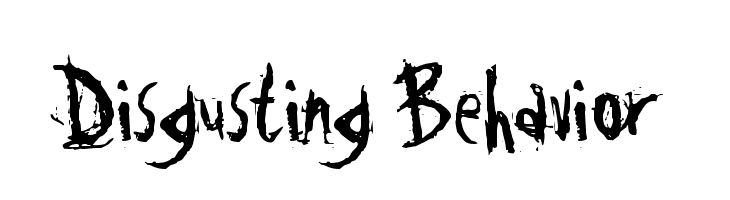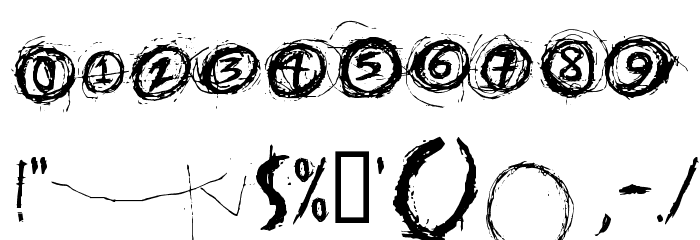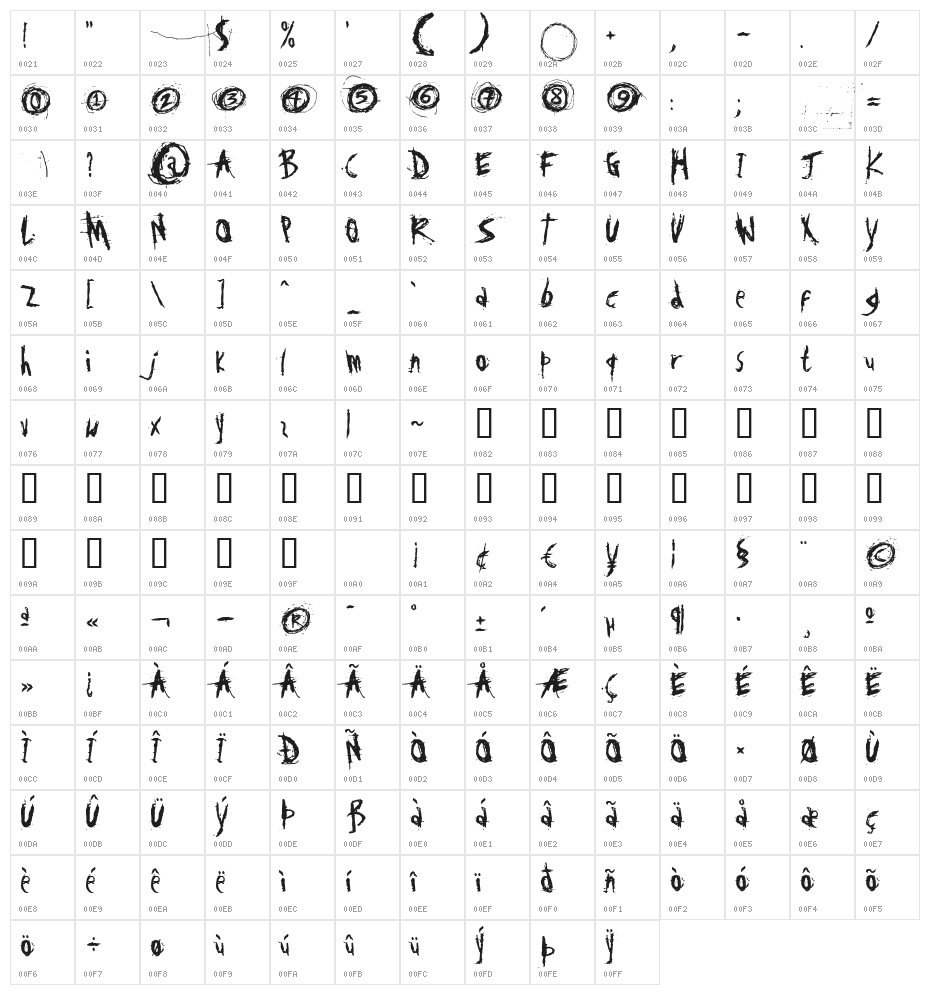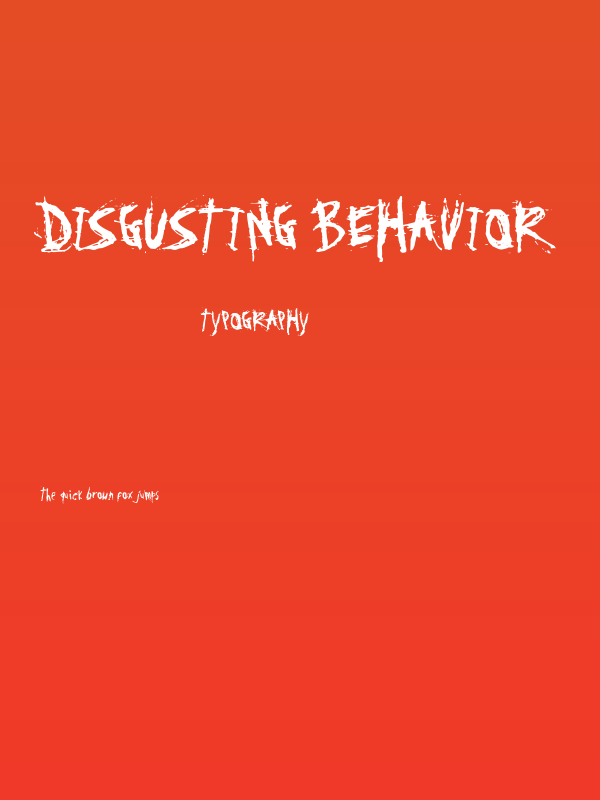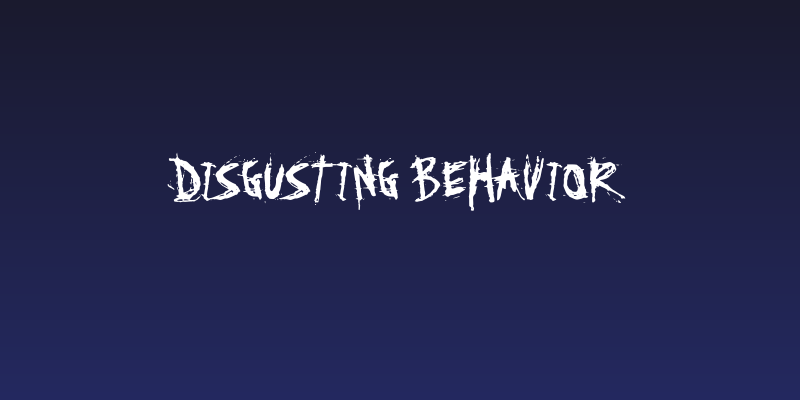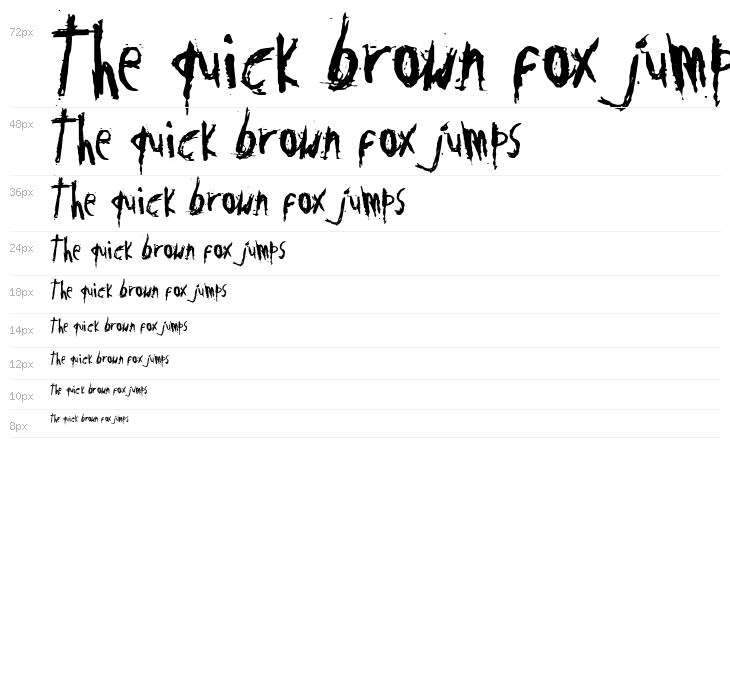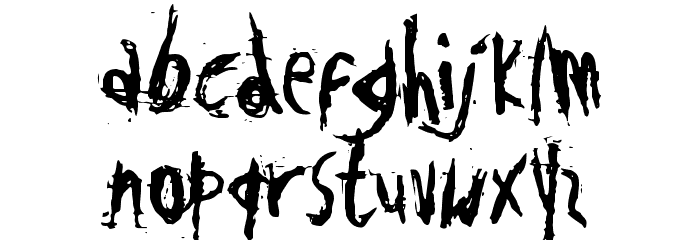
Disgusting Behavior Font
| Gesamtstil | Grunge, Edgy, Rebellious |
| Anwendungsfall | Headlines, Posters, Branding |
| Vorgeschlagene Projekte | Ideal for album covers, edgy posters, streetwear branding, or any project needing a bold, unconventional look. |